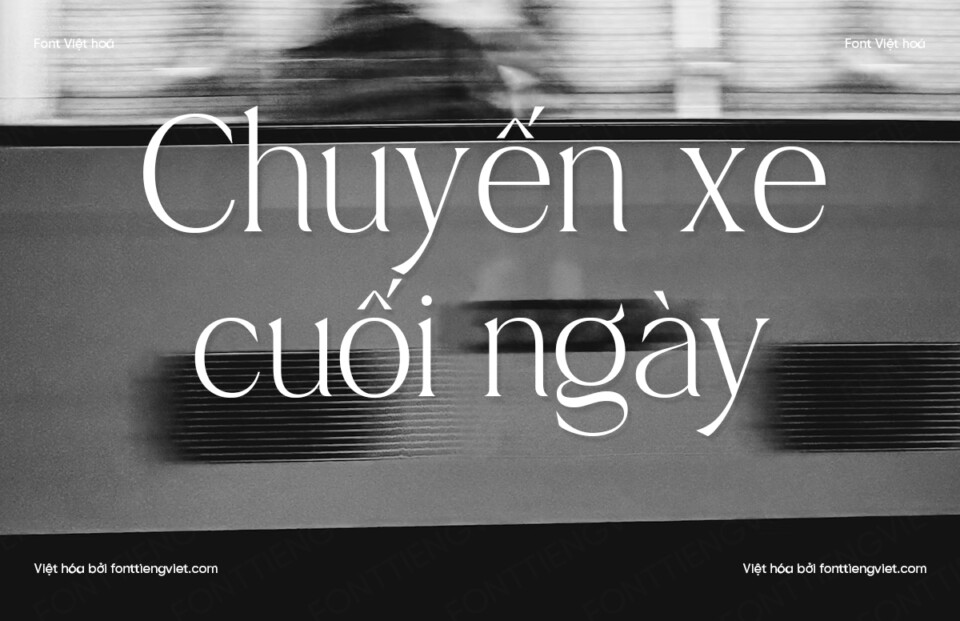
Font Việt hóa 1FTV VIP Brikey Moura
Giới thiệu về Font Việt hóa 1FTV VIP Brikey Moura trong thiết kế đồ họa
Trong thế giới sáng tạo, việc lựa chọn một bộ Font Miễn Phí chất lượng luôn là ưu tiên hàng đầu của các nhà thiết kế chuyên nghiệp. Font Việt hóa 1FTV VIP Brikey Moura xuất hiện như một làn gió mới, mang đến sự kết hợp hoàn hảo giữa nét hiện đại và phong cách cổ điển đầy tinh tế. Đây là bộ phông chữ được tinh chỉnh kỹ lưỡng về dấu tiếng Việt, giúp người dùng tại Việt Nam dễ dàng ứng dụng vào các dự án truyền thông mà không lo lỗi hiển thị. Với đường nét thanh mảnh nhưng chắc chắn, Brikey Moura không chỉ đơn thuần là công cụ soạn thảo mà còn là linh hồn của những tác phẩm nghệ thuật thị giác đẳng cấp.
Đặc điểm nổi bật của bộ Font Việt hóa 1FTV VIP Brikey Moura
Điểm thu hút nhất của Font Việt hóa 1FTV VIP Brikey Moura chính là cấu trúc ký tự độc đáo với các đường cong mềm mại và khoảng cách chữ được tối ưu hóa. Bộ font này thuộc phân khúc “VIP” nhờ sự đa dạng trong các biến thể từ Regular đến Bold, cho phép bạn linh hoạt thay đổi sắc thái thiết kế từ nhẹ nhàng, bay bổng đến mạnh mẽ, ấn tượng. Đặc biệt, các ký tự dấu tiếng Việt được đội ngũ 1FTV thiết kế đồng nhất về độ dày và vị trí, đảm bảo tính thẩm mỹ cao nhất khi trình bày văn bản dài hoặc các tiêu đề khổ lớn.
Ứng dụng thực tế của Font Việt hóa 1FTV VIP Brikey Moura
Khả năng thích ứng của Font Việt hóa 1FTV VIP Brikey Moura là vô hạn, phù hợp với nhiều lĩnh vực khác nhau trong đời sống. Trong lĩnh vực xây dựng thương hiệu, bạn có thể sử dụng font chữ này để thiết kế logo cho các nhãn hàng thời trang cao cấp, mỹ phẩm hoặc trang sức. Sự sang trọng vốn có của Brikey Moura sẽ giúp thương hiệu ghi điểm tuyệt đối trong mắt khách hàng ngay từ cái nhìn đầu tiên. Ngoài ra, đối với các bạn học sinh và sinh viên, đây cũng là lựa chọn tuyệt vời để làm nổi bật các bài thuyết trình Slide hoặc trang trí bìa tiểu luận thêm phần chuyên nghiệp.
Lợi ích khi sử dụng Font Việt hóa 1FTV VIP Brikey Moura cho truyền thông
Sử dụng Font Việt hóa 1FTV VIP Brikey Moura trong các ấn phẩm quảng cáo như poster, banner hay giao diện website giúp cải thiện đáng kể trải nghiệm người dùng. Font chữ có độ đọc tốt trên cả màn hình kỹ thuật số và bản in, giúp thông điệp của bạn được truyền tải một cách rõ ràng và mạch lạc. Bên cạnh đó, việc sử dụng một bộ font đã được Việt hóa chuẩn chỉnh giúp tiết kiệm thời gian chỉnh sửa hậu kỳ, tạo điều kiện cho các designer tập trung tối đa vào việc sáng tạo ý tưởng mới mà không bị gò bó bởi các rào cản kỹ thuật về ngôn ngữ.
Tổng kết về giá trị của Font Việt hóa 1FTV VIP Brikey Moura